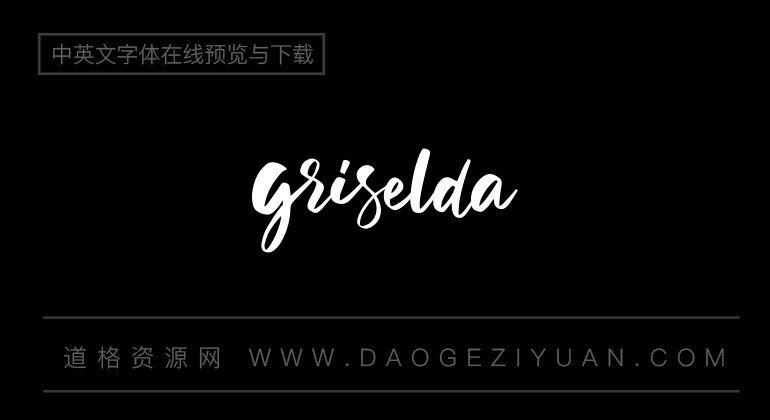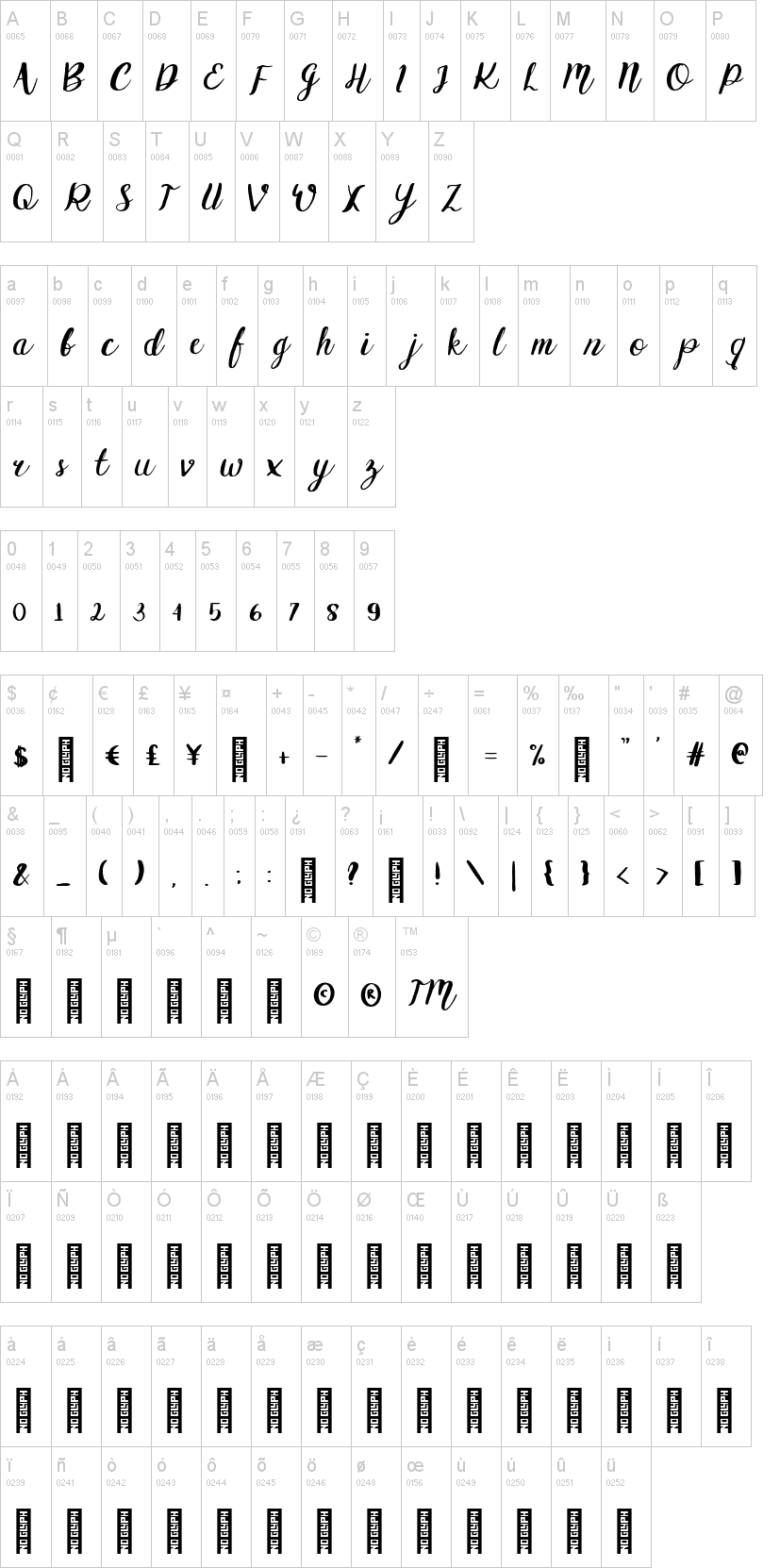
Griselda
Griselda 字体是一款经典的草书字体,由著名的西班牙设计师Juanjo López de la Cruz创作。这款字体以流畅的曲线,优雅的行距,细节丰富的笔画,以及简约的结构而闻名。它可以用于各种文字排版,并且可以让您的文字拥有更多的设计自由。Griselda 字体拥有多种字重,可以满足您的不同需求,同时也能够带来更加精致的视觉体验。
Griselda是一款非常不错的手写艺术字体,具有很好的视觉感,适合于文化类的宣传设计、商业类品牌的广告和产品包装设计以及个性化文字排版等较多场景。
Griselda字符映射图